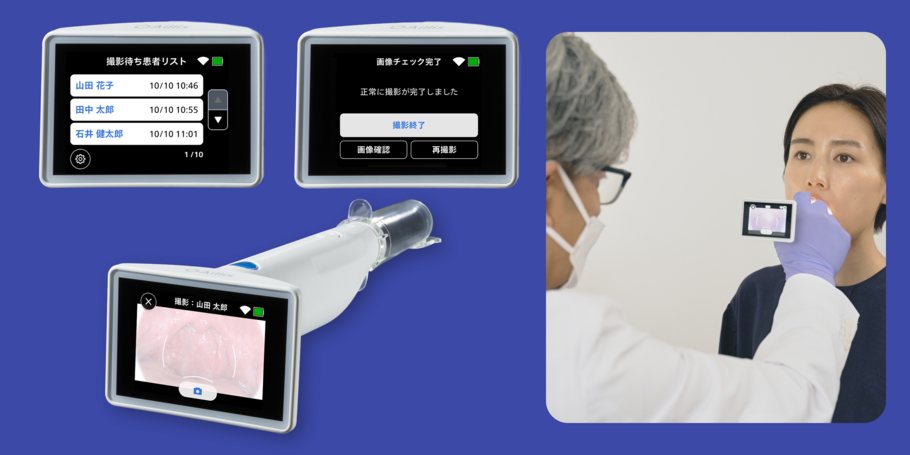
アイリス株式会社は、「みんなで共創できる、ひらかれた医療をつくる。」をミッションに掲げ、深層学習(人工知能)の技術を活用し、医師のもつ匠の技をデジタル化するAI医療機器を開発しています。今回、たづがね角ゴシック Info が同社の咽頭内視鏡システムのインターフェイスに採用されました。この製品は、のどを撮影した写真と問診情報等を解析して感染症に特徴的な所見や症状等を判定するAI搭載の機器で、医師による感染症診断に用いられます。
医療機器の表示に使われるフォントは、瞬時に読み取れることと読み間違えないことが重要です。患者さんの安全や命にかかわるため、医師が安全に機器を操作できるユーザビリティが最優先されます。
本医療機器の場合は、2.4インチ(約53 x 30 mm)の非常に小さな画面で20ピクセルのサイズで文字を表示した時の読みやすさが求められました。いくつかの書体で見え方を検討した結果、小さな文字サイズでも素早く正確に判読できた、たづがね角ゴシック Info が選ばれました。
たづがね角ゴシック Info は、Neue Frutiger に合わせて制作された和文書体、たづがね角ゴシックをベースに、ディスプレイ上で情報を素早く伝えられるように調整された書体です。小さな画面での可読性や判別性に優れているだけでなく、明るさや新しさを感じさせる書体であるところが、企業や製品のブランドともマッチしていました。
また、省リソースのデバイス上でも、スケーラブルフォントが使用できる Spark™ という技術を採用。画面上の文字サイズを拡大縮小してもスムーズに文字表示ができるため、たづがね角ゴシック Info の特徴である読みやすさを効果的に見せています。AI を搭載した医療機器の先進性と、誰もが使いやすい普遍性。たづがね角ゴシック Info は、「みんなで共創できる、ひらかれた医療をつくる。」というアイリスのミッションを的確に伝えています。